Кольорові шрифти гайд для початківців
Так що ж таке «кольоровий шрифт»? Це термін, який все частіше з'являється і починає набирати обертів, однак, незважаючи на використання в великих дизайн-проектах він все ще знаходиться в зародковому стані.
Такі виробники як Тypekit від Adobe вже почали випускати деякі колірні варіанти шрифтів з підтримкою браузера, так що є деякий рух у бік їх більш широкого використання. Деякі навіть називають кольорові шрифти "наступним великою подією в веб-дизайні".
Сьогодні ми розглянемо ближче даний тренд, і вирішуйте самі, наскільки грандіозним він стане. Або навпаки не стане.
Що таке кольоровий шрифт?
Кольорові шрифти практично є тим, як вони називаються. Шрифти, що складаються з декількох квітів, відтінків і градієнтів, текстур і прозорості. Ця шибко модна опція не просто додає колір до букв і написів: це специфічні шрифти з усіма включеними деталями.
Найбільша проблема з кольоровим шрифтом полягає в тому, що немає ніякого істинного стандарту його формату. І тут є підступ у всіх цих форматів файлів - векторні і SVG зображення можуть бути розширені з легкістю, але ось растрові версії можуть мати обмеження за розміром.
Насправді існує п'ять форматів:
- SBIX (Apple): Растрова версія зображення з власної підтримкою в системах Mac і iOS
- CBDT (Google): Растрова версія з підтримкою на базі Android
- COLR (Microsoft): Векторна версія з вбудованою підтримкою в системах Windows 8.1+
- SVG (W3C): Векторні і растрові версії
- OpenType SVG (Adobe / Mozilla): Векторні і растрові версії, які створюють форми SVG в шрифтах OpenType
З іншого боку, основні гравці вже почали приймати рекомендації по використанню таких шрифтів. Mozilla (основа веб-браузера Firefox) і Adobe погодилися з тим, що OpenType SVG є кращим форматом; інші ж все ще знаходяться в постійному русі, коли необхідно прийти до потрібного рішення.
Якщо ви хочете зрозуміти, як працюють ці шрифти і всі специфікації формату файлу, у Fontself є досить хороший приклад.
Як використовувати кольорові шрифти?
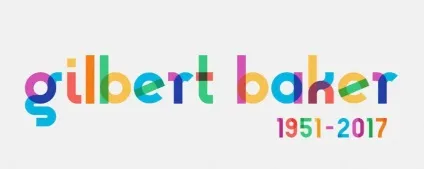
Одна з двох думок може виникнути у вашій голові, коли ви вперше бачите кольоровий шрифт:
- Вау, це жахливо!
- Круто! Я точно знаю, як це використовувати!
Незалежно від того, до якого табору ви ставитеся, є застосування, які ідеально підходять для кольорових шрифтів. Але ви повинні використовувати їх в розумних межах, адже кольорові шрифти призначені для найбільш економного використання.
Спробуйте кольоровий шрифт:
- Для техніки захоплення уваги для короткого слова
- Для елемента значка або логотипу
- Для лапки перед початком довгого блоку тексту
- Для зухвалого заголовка в дизайні з мінімальним стилем
- Фокусування на певному слові чи словах у великому блоці тексту
- Коли інша частина дизайну занадто проста
- Коли шрифт буде вашим основним елементом дизайну
- Коли проект вимагає чогось кумедного і незвичайного, щоб привернути увагу користувача
Як не використовувати кольорові шрифти
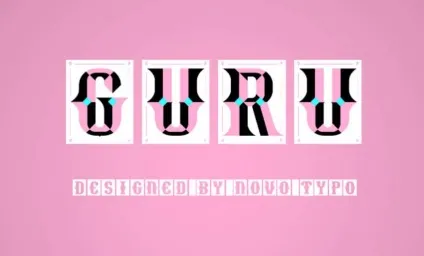
Не використовуйте кольоровий шрифт:
- З зображеннями або над зображеннями
- З забитим заднім фоном
- Для великої кількості тексту
- З безліччю інших технік дизайну, такими як анімація: зазвичай одного кольору досить для створення візуального впливу
- З іншими новинками або спеціальними шрифтами
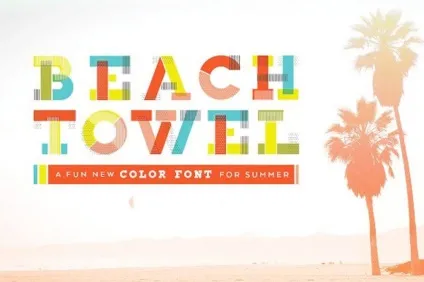
Тренд колірного шрифту починає набирати силу у деяких великих гравців в типографике. Формат SVG OpenType, прийнятий Adobe і Mozilla, може стати інструментом і форматом, який допоможе цій тенденції дійсно злітати. Adobe навіть недавно додав кольорові шрифти в Photoshop, також ви могли помітити деякі емодзі в палітрі символів.
Ось як Adobe пояснює OpenType SVG:
OpenType-SVG - це формат шрифту, в якому шрифт OpenType має всі або тільки деякі його гліфи, представлені в якості зображення SVG. Це дозволяє відображати кілька кольорів і градієнтів в одному гліфів. Через цих особливостей ми також посилаємося на шрифти OpenType-SVG як «кольорових шрифтів»
Шрифти OpenType-SVG дозволяють показувати текст з графічними якостями, зберігаючи при цьому можливість редагувати, індексувати або шукати. Вони також можуть містити функції OpenType, які допускають заміщення гліфа або альтернативні стилі гліфа.
Кольорові шрифти, такі як Trajan Color Concept і EmojiOne Color, будуть відображатися так само, як і звичайні шрифти в меню шрифтів ваших програм, але вони можуть не відображати весь свій потенціал, оскільки багато програм ще не мають повної підтримки колірних компонентів.
Якщо ваша програма не підтримує оформлення SVG в шрифтах, гліфи повертаються до простого чорного стилю. Колір може бути застосований до цього резервному стилю, оскільки він буде працювати як звичайний шрифт OpenType.
Спробуйте кольоровий шрифт
Якщо кольорові шрифти - це ваша річ, ви можете або завантажити кольоровий шрифт, щоб почати роботу, або створити свій власний, в залежності від типу проекту над яким працюєте.
Є деякі досить класні кольорові шрифти, які кричать, щоб ви використовували їх у вашому проекті сьогодні. Ось кілька шрифтів, щоб прискорити ваш творчий потік, плюс посилання на інші кольорові шрифти, використовувані вище:
Деякі дизайнери вважають, що ця тенденція дуже цікава і має реальне практичне застосування в друкованих проектах, таких як плакати або листівки. Проте, вони ще не зовсім переконані в ній, коли мова заходить про веб-проектах. Тільки час покаже, чи дійсно ця тенденція стала «наступною великою річчю в веб-дизайні» або черговий скороминущої примхою.